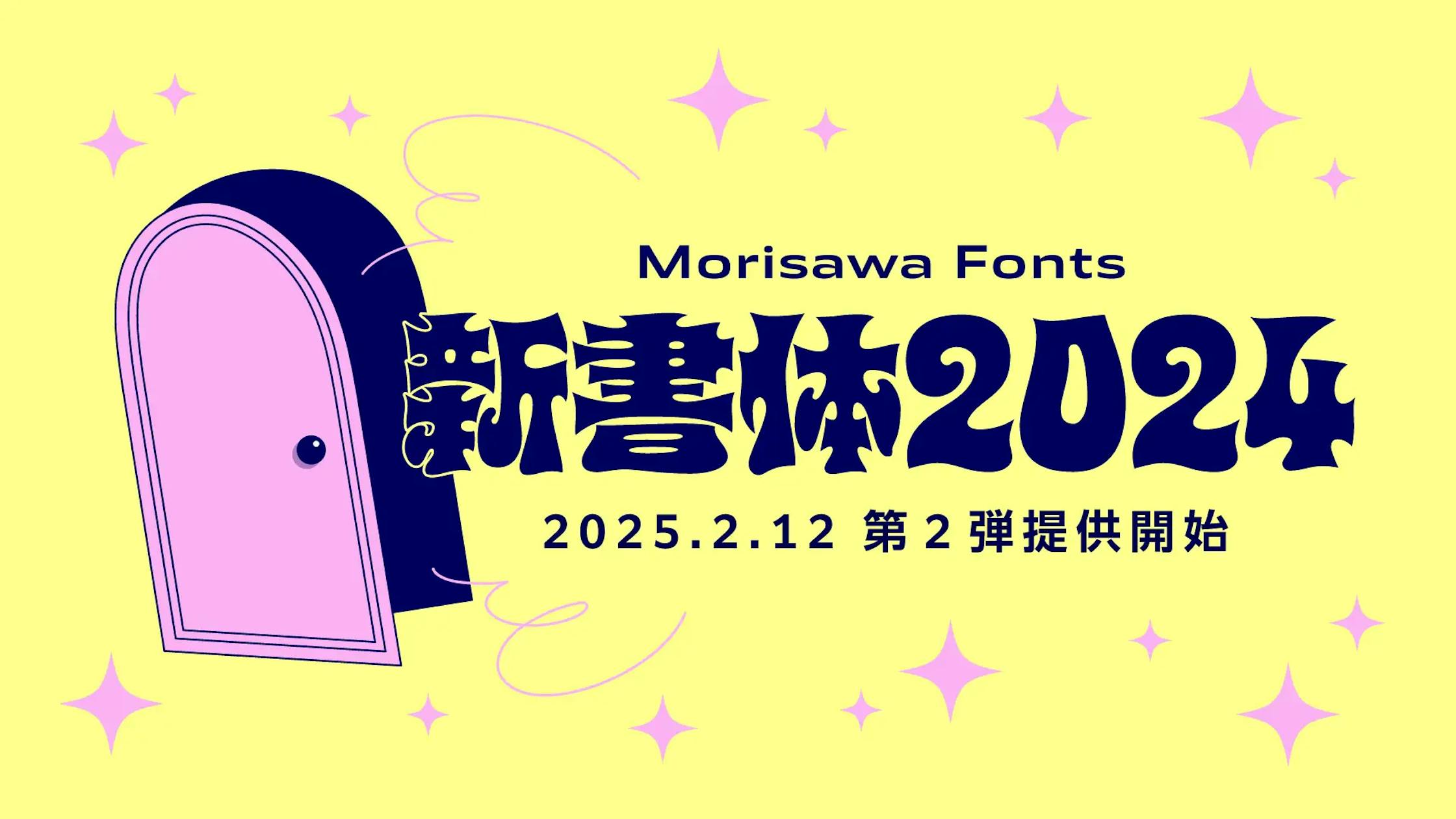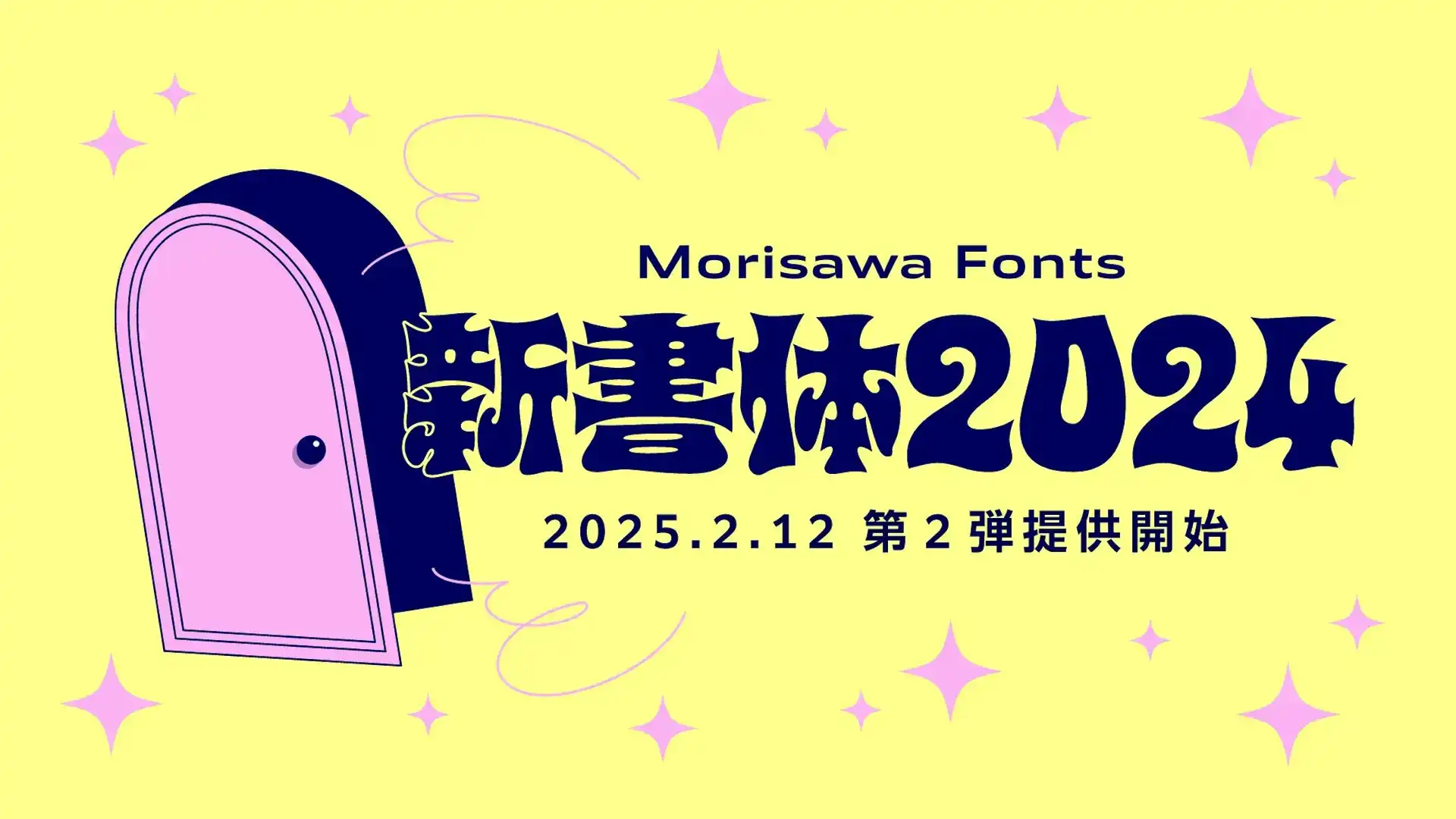
モリサワ、初のバリアブルフォントを含む新書体を2025年2月12日より提供開始
株式会社モリサワは、2025年2月12日午前11時より、Morisawa Fontsアップグレード2025年2月版の一環として、新書体第2弾を提供開始するとのこと。
今回のアップグレードでは合計37ファミリーが追加される。特に注目されるのは、モリサワにとって初のバリアブルフォントである「DriveFlux」で、シンプルかつシンメトリーな骨格と幾何学的ストロークが特徴。見出しなど、視覚的に注目を集めたい場面での使用が推奨されている。また、欧文スーパーファミリー「Role」にはインドや東南アジアで用いられる14の多言語展開ファミリーが追加。これにより、さらなる多言語対応が期待されるという。加えて、Clarimo UDシリーズにハングル書体が加わることで、さまざまな言語で統一感のあるデザイン表現が可能になるとのこと。
アメリカに拠点を持つ書体ライブラリOccupant Fontsからの新しい書体も登場。例えば、機械的で無骨なスラブセリフ体「Dispatch 2」や、見出しに適した重厚感のあるサンセリフ体「Magmatic」などが挙げられる。従来のモリサワ書体に加え、これらの書体もぜひアクティベートして利用してみたい。